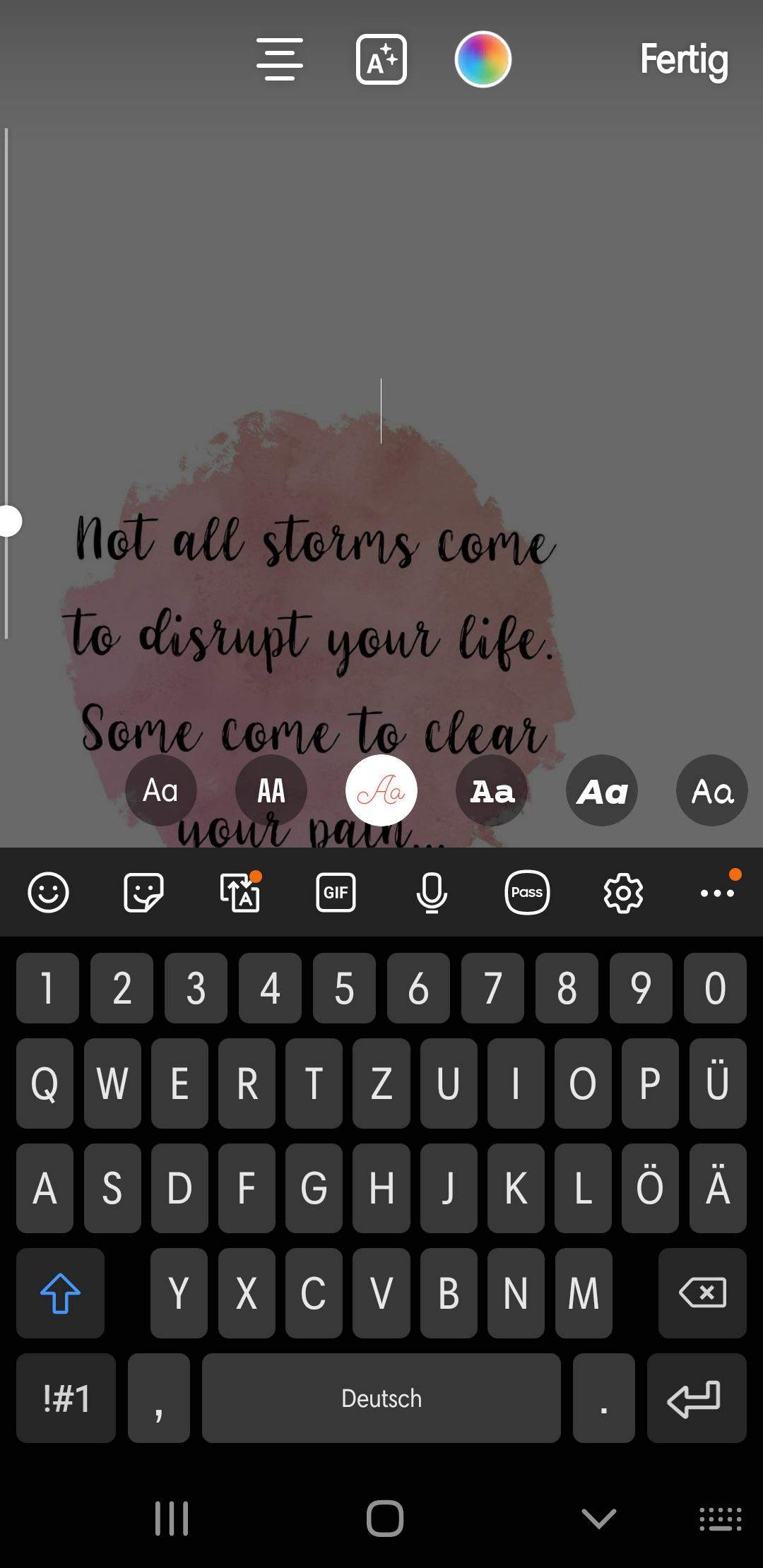
Instagram Andere Schriftart Anzeigen
Ein anderes nützliches Online-Tool ist der Cool . Hier kannst Du Texte und deine Biografie bei Instagram stylen und gestalten wie Du willst.??Heute geht es einmal wieder darum, wie du deine alltäglichen Instagram-Stories etwas aufpeppen und attraktiver aussehen lässt. Ein neues Fenster öffnet sich, in . Auch die Schriftart „Freight Sans“ . Klicken Sie auf „Schrifteinstellungen“. Instagram-Story-Trick Schrift . Diese Schriftarten können verwendet werden, um auf Seiten von Social-Media-Netzwerken wie Instagram angezeigt zu werden, wodurch Sie sich von der Masse abheben und einen anderen Charakter haben.So ändern Sie die Schrift in Instagram und Android und iOS. Jetzt hier Text eingeben im Schriftgenerator!Geben Sie dann Ihren Text ein und ändern Sie, falls nötig, mit dem Schieberegler am linken Bildschirmrand dessen Größe.
Instagram-Schriftarten
Instagram Schriftart in Bio ändern
Instagram Story: Schriftart ändern
Wenn Sie neue Schriftarten auf Ihrem iPhone 12 verwenden möchten, erklärt unser Ratgeber, welche Möglichkeiten Sie haben. Hier tippst Du in das erste Feld einfach deinen Instagram-Namen ein und darunter erscheint der Name dann in . Wenn Du einen Text auf ein Bild in der Story .Etwas herausfordernder ist hingegen die Auswahl einer anderen Schriftart, die nur durch das Einfügen der jeweiligen Unicode-Zeichen in die Instagram-Bildunterschrift möglich ist. Hier unterstützen alle Instagram- Schriftarten jede Art von Social-Media- und Gaming-Konto ohne Fehler. Das Motto sollte aber stets „weniger ist mehr“ sein, denn diverse Schriftarten, Emojis und kursive Wörter verwirren mehr, als dass sie einen Mehrwert schaffen. This is a simple generator that you can use to make fonts for Instagram.
Welche Schriftart wird bei Instagram verwendet
In diesem Artikel erfahren Sie, wie Sie Texte in Instagram Reels platzieren, um die Aufmerksamkeit Ihrer Zuschauer zu erregen und die Wirksamkeit Ihrer Videos zu verbessern. Die Schriftverwaltung. Alles, was Sie tun müssen, ist, auf die Website zu gehen, Text in das Feld einzugeben und aus der Liste der Fonts auszuwählen, die unter dem Feld angezeigt . Eine Option Text kopieren wird angezeigt.Schriftverwaltung.
So einfach kannst du die Schriftart auf Social Media ändern
Einige Schriften sind fett, andere kursiv und einige sogar durchgestrichen und auf dem Kopf geschrieben. Um mehr Individualität in dein Profil auf Instagram zu . Wenn du darauf klickst, wird ein Menü angezeigt, in dem du die Option „Story teilen“ auswählen kannst. Allerdings funktioniert das nicht immer reibungslos, weshalb wir verraten, worauf du achten sollest. Font-Generator. Wenn du darauf klickst, wird ein neuer Beitrag erstellt, in dem du das .Die normale Instagram Bio und generell der ganze Text, den du unter einem Post verfassen kannst wird in der Standardschriftart „Neue Helvetica“ angezeigt.21 Instagram-Hacks für eine erfolgreiche Nutzung. Es erscheint eine große Palette an Farben.
Die letzte Möglichkeit, Schriftart in deiner Instagram Bio zu ändern, die ich dir vorstellen möchte ist die App Fonts für Instagram. Ich habe daraufhin diese Schrift mal auf meinen Adobe und Mac Programmen verwendet, dort funktioniert sie einwandfrei. Dazu markierst du das Wort, klickst auf den Pfeil nach unten (1) und wählst „Tastatur-Eingabe . Ich habe es selbst auch schon mal ausprobiert und habe nun für diesen Beitrag recherchiert, um euch die besten Methoden vorzustellen! Diese . Wichtige Faktoren, die Sie berücksichtigen sollten, bevor Sie sich entscheiden, Ihren Instagram-Namen und/oder Benutzernamen zu ändern. Kommentare fixieren und verbergen.
Instagram Schrift ändern: So geht´s in der Bio
Dennoch hat man die Möglichkeit die Schriftart von dem Namen und der Profilbeschreibung in Steam zu ändern, indem man Sonderzeichen aus der Zeichentabelle verwendet.Aktuell kann man bei Instagram die Schriftart von dem Namen teilweise über solche Schriftgeneratoren ändern. Name und Schrift verändern.Vorab sei gesagt, dass sich jede Schriftart anders verhält. In diesem Fall, wird die Schriftart nur registriert, beim Neustart von Windows wird diese nicht mehr angezeigt, hier sehen Sie, wie Sie sie ohne installieren in Windows 11, 10, 8. Alle auf Ihrem PC installierten Schriftarten sind in einem einzigen Fenster verfügbar.Nun kann man den Link-Text und die Farbe der Sticker anpassen. Mehr über Formatierung und die angezeigte Schrift erfahren Sie bei uns im TippCenter.Die Schriftart kann nicht an allen Android-Smartphones über die Einstellungen geändert werden.de und tippe in dem ersten Feld den Text ein, den Du bei Instagram fett schreiben möchtest. Es gibt aber noch andere Wege, um zum Ziel zu kommen. Suchvorschläge löschen. Instagram: So kannst du die Schriftart ändern . Du kannst einen Text HIER eingeben und in coole Schriftarten elegant umwandeln. Klicken Sie auf „Schriftarten“. Simply put your normal text in the first box and fonts for Instagram bio/captions/etc.
Instagram: So fügen Sie Ihren Fotos Texte hinzu
Hashtags folgen. die App Cool Fonts for Instagram. Zum Ändern der Schriftart wischen Sie unten durch die verschiedenen Aa . Erfahre mehr über Werbung auf Instagram und unsere Werbeanzeigenformate. Wählen Sie die richtige Schriftart.Die Schriftarten können Sie nur bedingt in WhatsApp ändern. Gib den Text ein, wandle ihn in die gewünschte Schriftart um und kopiere ihn in die Zwischenablage.
Werbung auf Instagram
Als Workaround kannst du aber in Überschriften und Absätzen einzelne Wörter z.Um sicherzugehen, dass das Ändern der Instagram Bio Schrift auch bei anderen Profilen korrekt angezeigt wirst, lässt Du dies am besten durch einen Bekannten überprüfen.Fonts for Instagram. Weshalb ich darauf . Windows 7 Schriftarten Übersicht.Leider lässt sich bei Instagram selbst nicht die Schrift ändern, doch glücklicherweise unterstützt die App dennoch andere Schriftarten.
Schriftarten Generator
Im Schriftarten Generator lassen sich auf diese Weise viele schöne Schriften online erstellen und kopieren. Wir zeigen Ihnen, wie Sie auf dem Kindle die Schriftart ändern können. Auf dieser Seite können Sie Ihren Text eingeben und ihn sofort in verschiedenen Schriftarten sehen: Es gibt Optionen in Fett und Kursiv und Sie können sogar Ihre eigene Schriftart kreieren.Mit FontViewOK kann man Schriftarten anzeigen, bzw. Dazu gehören zum Großteil Bildunterschriften und Kommentare. Das bedeutet also, wenn du für den Text eines Dokuments die Schriftart veränderst, können sich auch die Abstände und dementsprechend die gesamte Erscheinung ändern.
Wenn ich nun die neue Font in Office verwenden möchte, wird Sie mir zwar richtig in der Schriftauswahl angezeigt, sobald ich diese aber ausgewählt habe, wird sie anders dargestellt (siehe Bilder). Lesen Sie hier, wie Sie das Aussehen .Von Android-Geräten verwendete Instagram-Schriftarten Android-Geräte, darunter Samsung, Xiaomi, Oppo, Redmi und OnePlus, verwenden Roboto als Standardschriftart für Instagram.